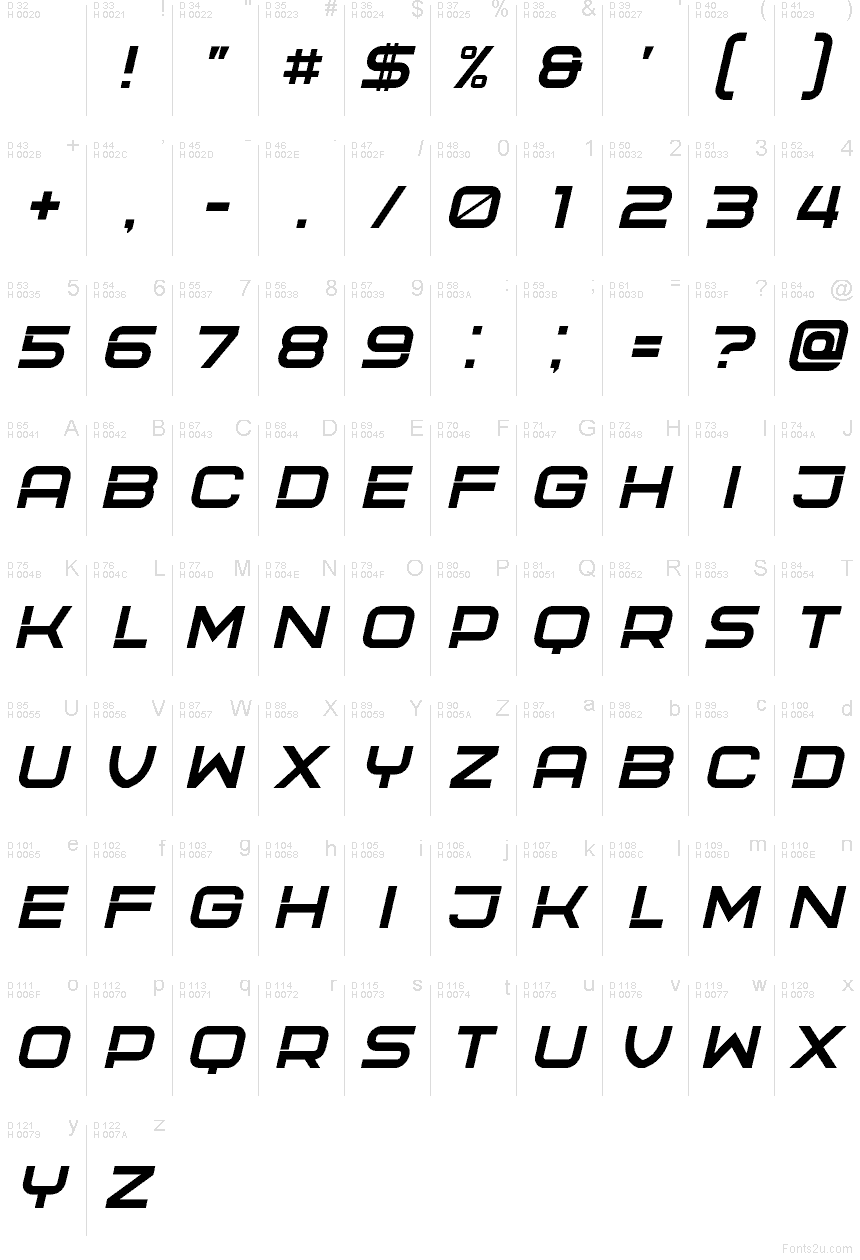
Haine Italic od Vladimira Nikolice je bezplatné techno písmo typu display, které vyniká ostrým náklonem vpřed a dlouhými paralelními řezy, jež udržují písmena v neustálém pohybu. Design působí jako promyšlený systém úseček, diagonál a zaoblených rohů, což mu dodává rychlý elektronický rytmus namísto neutrálního geometrického dojmu.
Tato struktura skvěle funguje u herních titulů, hudebních vizuálů, sci-fi plakátů, esportového brandingu nebo bannerů aplikací, kde rychlý směrový tah pomáhá textu ukotvit celý layout. Font se hodí i pro tvorbu log nebo video náhledů, zejména pokud hledáte elegantní digitální styl, aniž byste museli spoléhat na wireframe efekty nebo klišé futuristické triky.
Haine